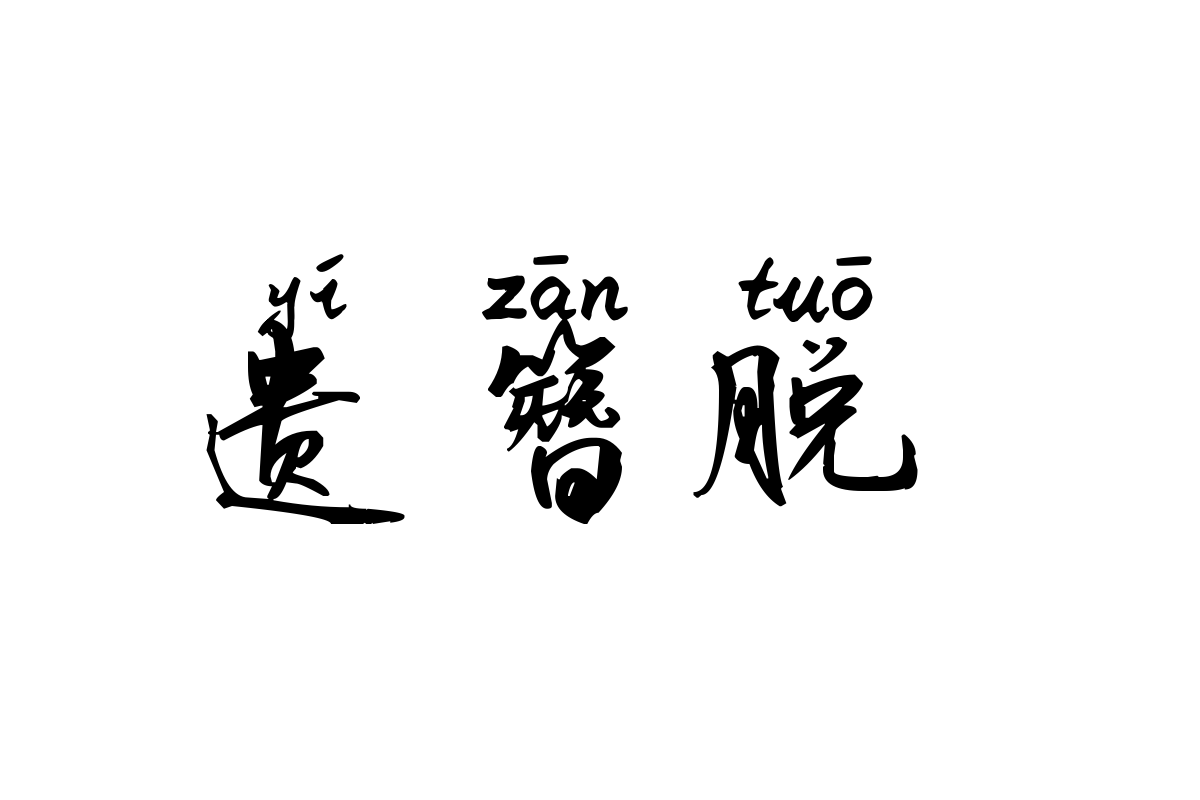
米开俊美行楷拼音体是一种独特的书法字体,它融合了中国传统的行楷和拼音字母的特点。这种字体的特点是笔画流畅、结构紧凑,给人一种简洁明快的感觉。
米开俊美行楷拼音体的笔画粗细适中,既有行楷的流畅感,又有拼音字母的清晰性。在书写时,笔画连接自然,没有生硬的痕迹,给人一种舒适的感觉。同时,这种字体还具有一定的装饰性,笔画之间可以穿插一些装饰性的笔画,使整个字体更加美观。
此外,米开俊美行楷拼音体还具有一定的实用性。由于它的笔画结构和拼音字母相似,因此对于学习拼音的人来说,这种字体可以作为一种辅助工具,帮助他们更好地学习和掌握拼音。同时,对于喜欢书法的人来说,这种字体也是一个很好的选择,因为它既具有书法的艺术性,又具有拼音的实用性。
总之,米开俊美行楷拼音体是一种独具特色的书法字体,它融合了传统和现代的元素,既有艺术性,又有实用性。